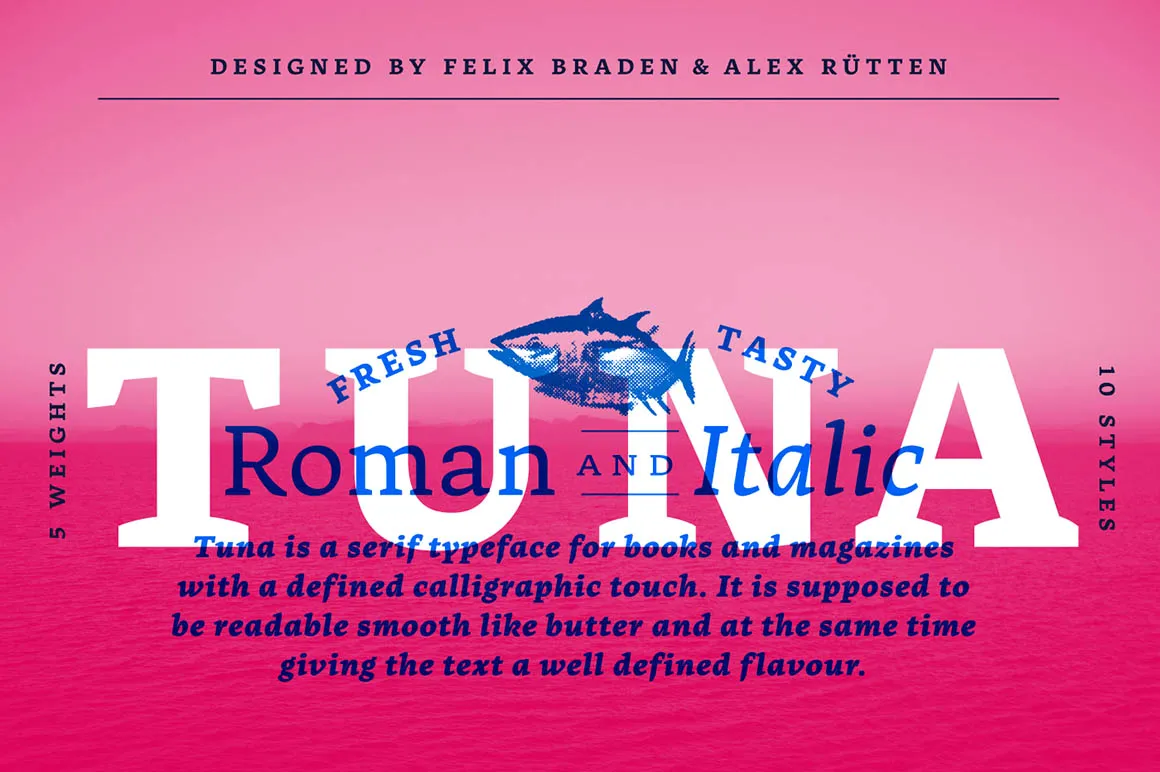
Introduzimos a Tuna Font Family, uma família serif criada pela Ligature Inc. A Tuna é essencialmente um tipo de texto contemporâneo. Suas linhas reticentes e estilo de chifre são perfeitamente adaptadas para o seu uso em conteúdo online, mantendo fiel às raízes da escrita e tipografia ao mesmo tempo que nos permite continuar a ler “Anna Karenina” até as quatro horas da manhã no nosso Kindle. Completando sua paleta é também uma fonte de título, Tuna é perfeito para textos que precisam de um pouco mais de destaque e elegância na página. Seja você designer de revistas, desenvolvedor web ou editor de fotos, a Tuna tem o seu lugar. Transforme sua página em algo realmente especial com esta incrível fonte.